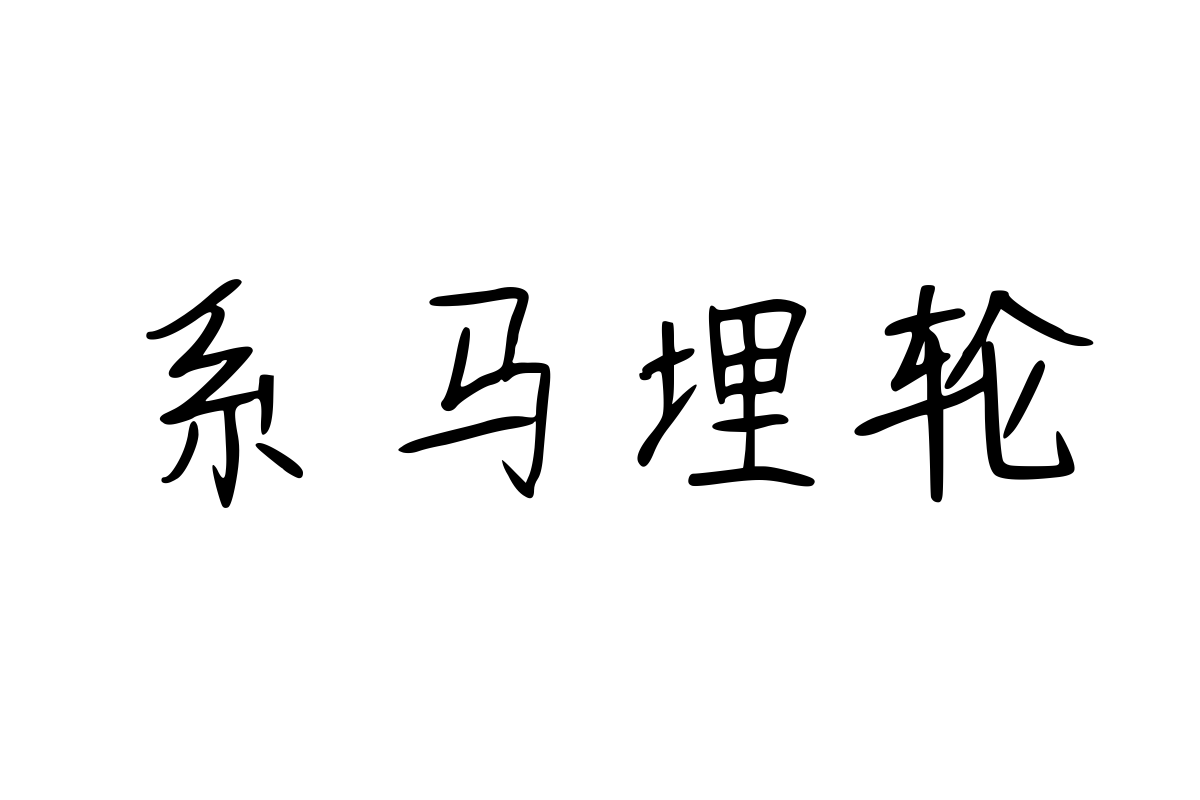
思雨把酒夜话是一款具有独特韵味的中文字体,它融合了传统书法与现代设计元素,展现出一种优雅而不失个性的风格。这款字体适用于各种需要表达深情、浪漫或怀旧情感的场合,如诗歌、散文、小说等文学作品的创作,以及各类广告、海报、包装设计等商业用途。
思雨把酒夜话的字形结构独特,笔画流畅自然,既有古典之美,又不失现代感。它的线条粗细适中,既有力度,又不失柔美,给人以视觉上的享受。同时,这款字体还注重细节的处理,如字间距、行间距等,使得整体布局更加和谐、美观。
在色彩搭配方面,思雨把酒夜话采用了柔和的色彩调,既符合其浪漫、怀旧的主题,又能营造出温馨、舒适的氛围。无论是黑色还是白色,都能展现出其独特的魅力。此外,这款字体还提供了多种字重选择,以满足不同场景的需求。
总之,思雨把酒夜话是一款独具匠心的中文字体,它以其独特的韵味和风格赢得了广大用户的喜爱。无论是用于文学作品的创作,还是用于商业设计的展示,都能展现出其独特的魅力。